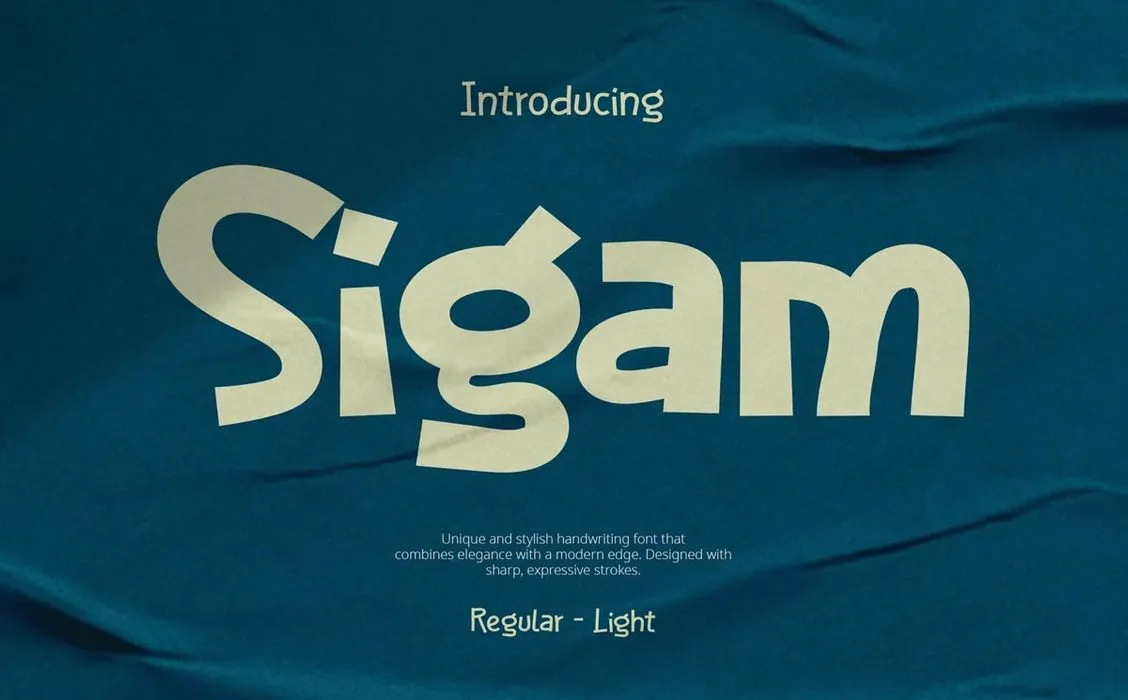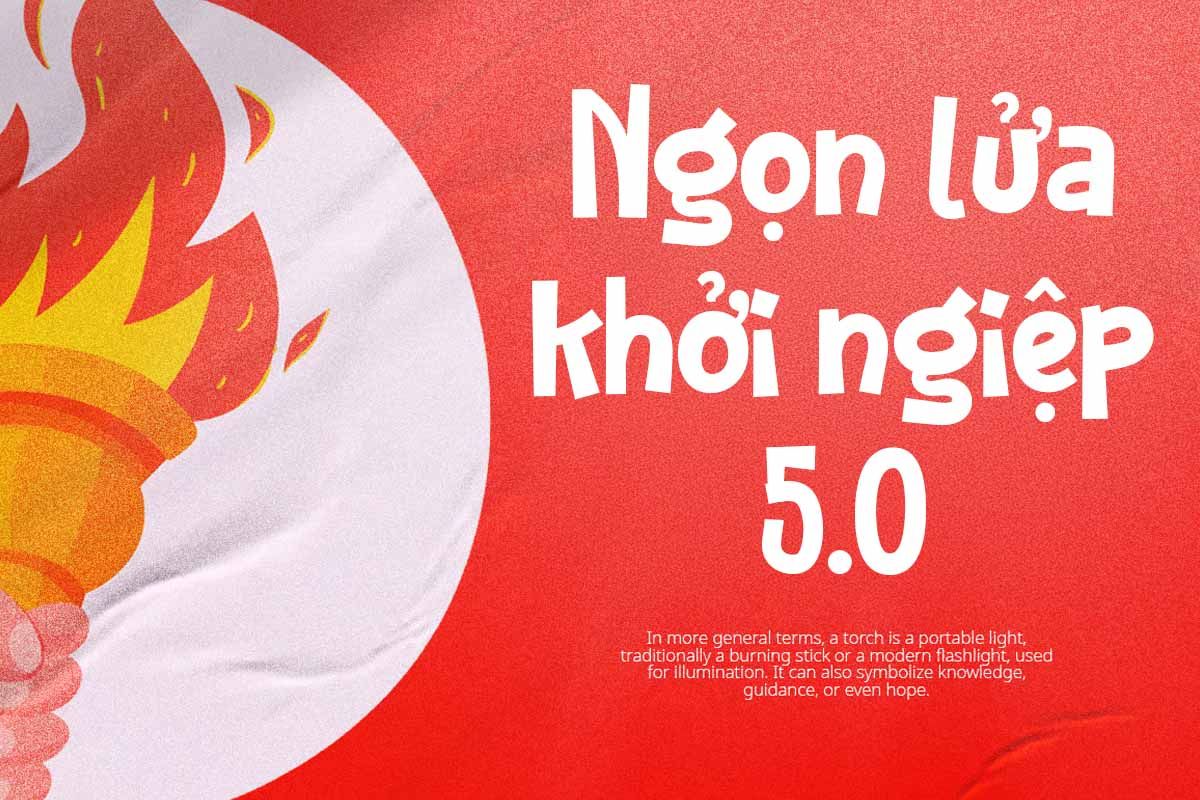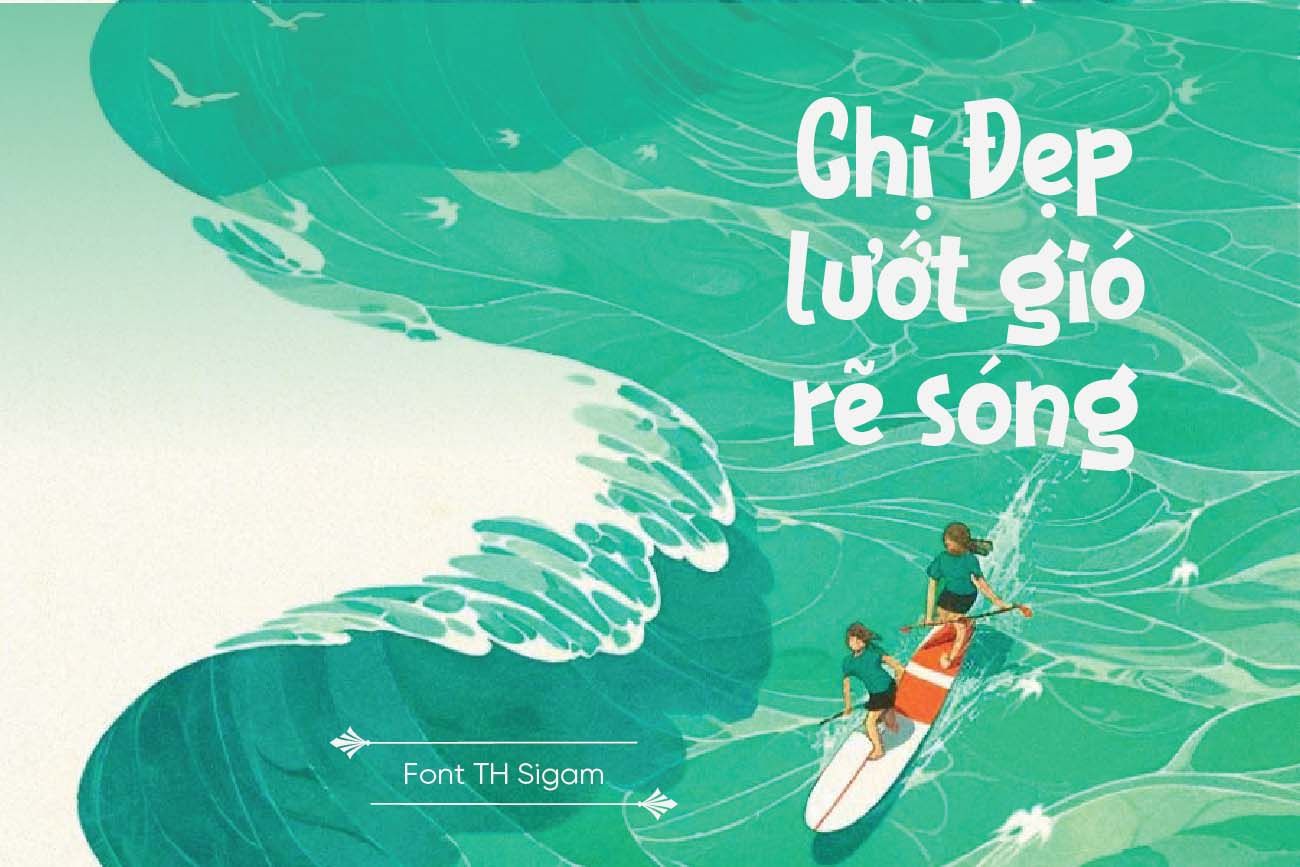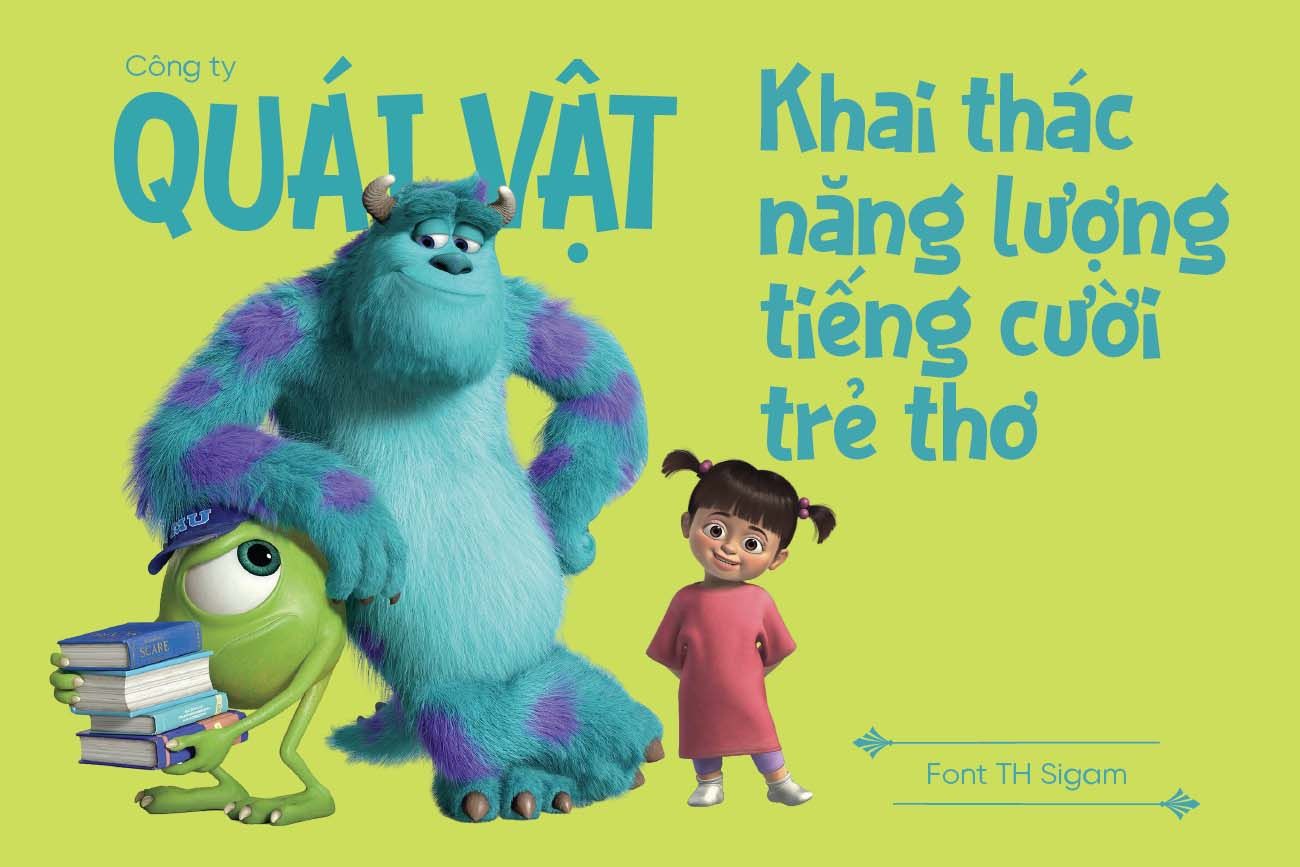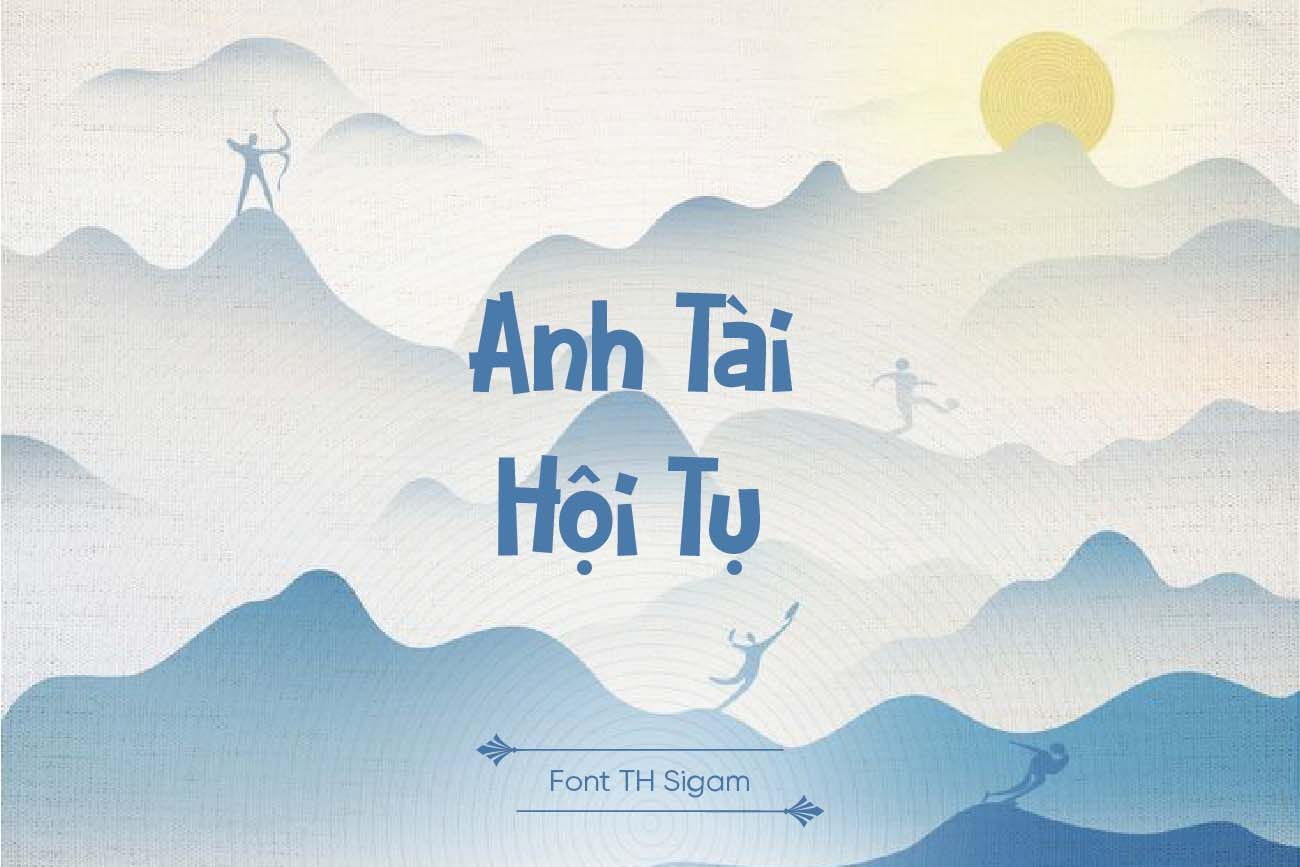
Không giống với những kiểu chữ nghiêm túc hay cầu kỳ, TH Sigam mang đậm hơi thở tự do của nét viết tay hiện đại, nhưng được tinh chỉnh để có độ cân đối và dễ đọc. Mỗi ký tự đều có độ nhún, nghiêng nhẹ vừa phải tạo cảm giác linh hoạt, như thể đang chuyển động – rất phù hợp với các chủ đề hoạt hình, trẻ em hoặc các sản phẩm mang tính giải trí. Nhờ đó, TH Sigam thường được sử dụng trong thiết kế bìa truyện tranh, poster phim, game, logo thương hiệu sáng tạo hoặc tiêu đề video YouTube hướng đến đối tượng trẻ.
Font gồm hai kiểu chính là Regular và Light, giúp nhà thiết kế dễ dàng phối hợp trong cùng một layout hoặc thay đổi sắc thái tuỳ bối cảnh sử dụng. Bộ font được Việt hóa đầy đủ, hỗ trợ tất cả dấu tiếng Việt theo chuẩn Unicode, tương thích hoàn toàn với các phần mềm thiết kế phổ biến như Photoshop, Illustrator, Corel, Canva, Figma,… Việc Việt hóa tỉ mỉ của Phạm Sơn giúp TH Sigam giữ nguyên tinh thần hoạt hình của bản gốc nhưng vẫn phù hợp với người dùng Việt, đảm bảo tính thẩm mỹ và cân bằng trong từng con chữ.
TH Sigam không chỉ là một font chữ, mà còn là một “nhân vật” mang cá tính riêng – vui nhộn, gần gũi và tràn đầy sức sống. Nếu bạn đang tìm kiếm một font chữ hoạt hình dễ thương để làm nổi bật thiết kế của mình, TH Sigam chắc chắn sẽ là lựa chọn hoàn hảo, giúp tác phẩm của bạn trở nên bắt mắt, đáng nhớ và đầy cảm xúc.